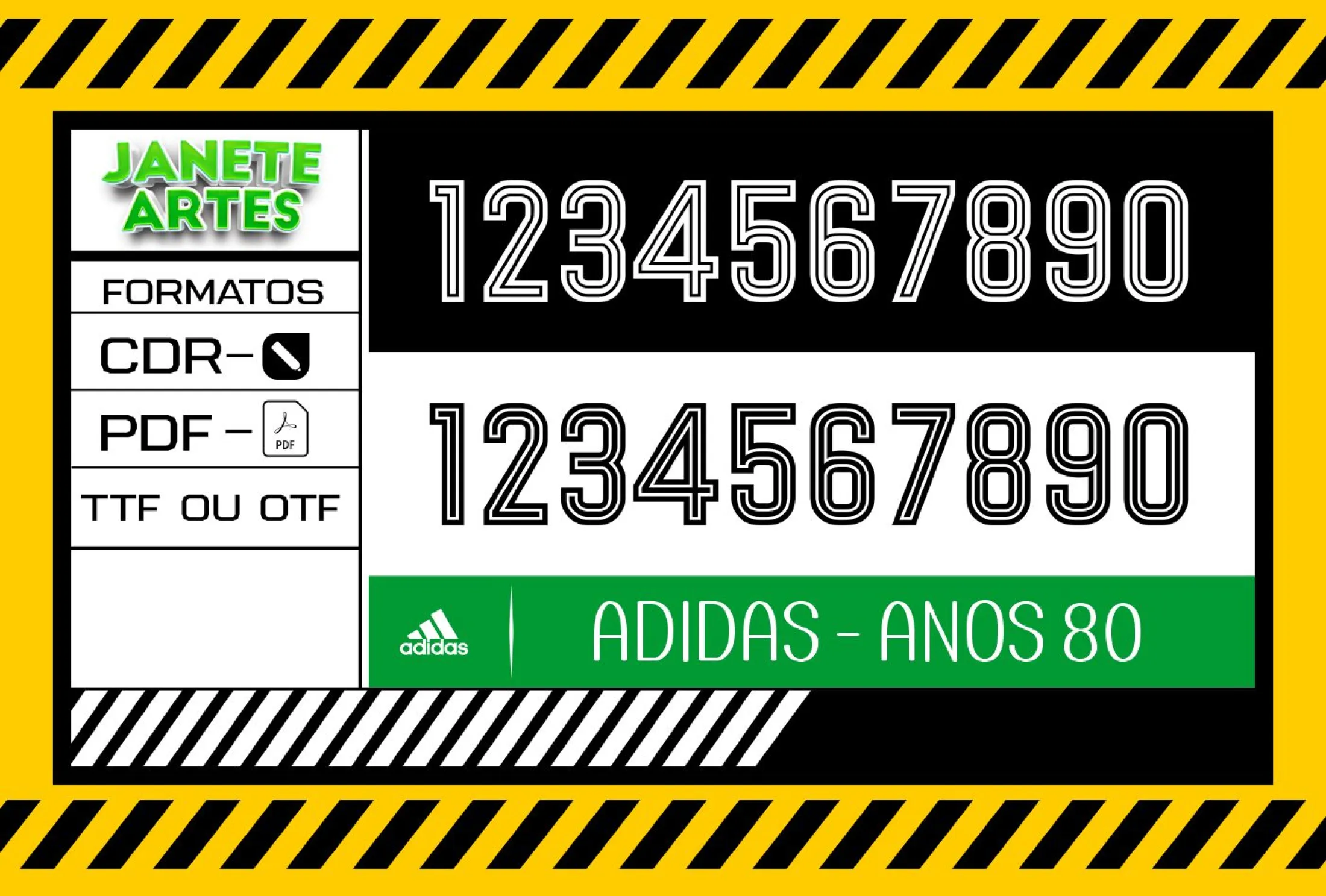
Fonte de Time Tipografia Adidas Anos 80
Uma viagem ao passado com a Fonte de Time Tipografia Adidas Anos 80
Imagine aquela emoção de voltar aos anos 80, quando o estilo das camisas de times era marcante e cheio de personalidade. João sempre foi apaixonado por esportes e design vintage. Um dia, ele decidiu criar camisetas para o seu grupo de amigos que curtem futebol com um toque retrô. Encontrou a Fonte de Time Tipografia Adidas Anos 80 e tudo mudou. As peças ficaram incríveis, atraindo olhares e despertando conversas sobre a nostalgia dos anos dourados do esporte. Uma lembrança que agora poderia levar para qualquer lugar!
• Fonte que reproduz fielmente a tipografia Adidas dos anos 80, ideal para times, eventos e projetos especiais.
• Aplicação fácil em camisetas, camisas e blusas para um estilo retrô autêntico.